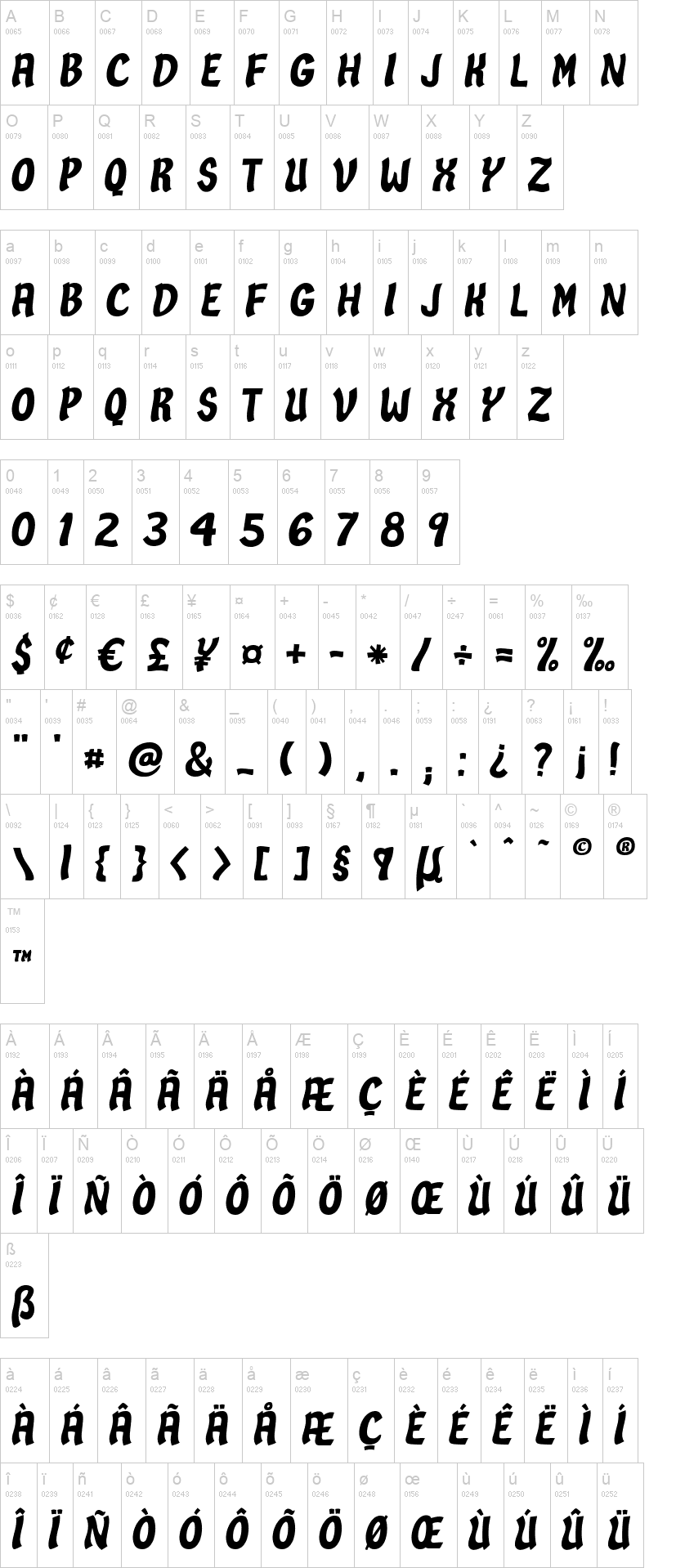
Note of the authorSuburbana é uma tipografia brasileira, criada pelo designer gráfico Fernando PJ no ano de 2003, inspirada no trabalhos dos pintores de letras populares na cidade de Salvador (Bahia, Brasil).
Suburbana is a Brazilian typography, created by graphic designer Fernando PJ in 2003, inspired by the work of the popular letters painters in the city of Salvador (Bahia, Brazil).